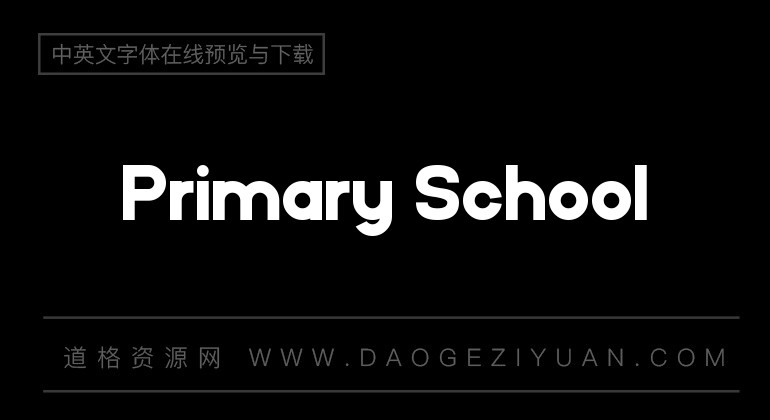
Primary School字体是一款拥有简洁、清新、可爱的设计风格的字体,它以简洁的线条和清晰的字形结合在一起,拥有一种简约而又可爱的特质。它主要用于小学生的文字排版,可以让小朋友们更容易理解字体的排版,从而更好地表达文字的意思。内容介绍
Primary School是一款非常不错的手写艺术字体,具有很好的视觉感,适合于文化类的宣传设计、商业类品牌的广告和产品包装设计以及个性化文字排版等较多场景。